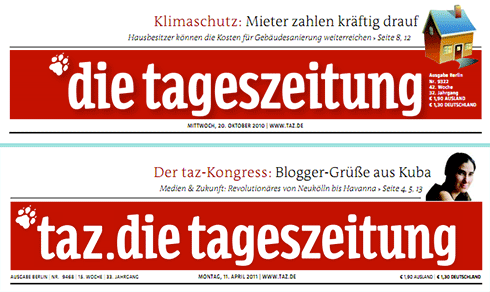
Seit gestern prangt ein neues Logo auf der Titelseite der taz. Sie heißt jetzt nicht mehr nur »die tageszeitung«, sondern »taz.die tageszeitung«. »Die Titelkopfveränderung ist ein großer Schritt für uns gewesen« heißt es im hauseigenen Blog. In den vergangenen Jahren habe die taz unzählige Logos entwickelt: für die Stiftung, den Shop, Kaffee, Genossenschaft, vielfältige redaktionelle Produkte, Reisen und vieles mehr. Dabei sei die visuelle Markenarchitektur eher gewuchert als gewachsen. Deshalb sei derMoment gekommen, die Marken zu sortieren und ihre Verwandtschaft auch visuell herzustellen.
Weiter schreibt Nina Schoenlan im taz-Blog: »Zu jedem Logo hier im Haus gehören Menschen, die dieses Logo gemacht haben, das Projekt hinter dem Logo mit Leben erfüllt haben und zum Strahlen brachten. Deswegen haben wir keine Logos entfernt. Alles wird über einen Punkt mit der taz verbunden. Wir haben mit der Agentur Metadesign Bildmarken integriert, die ›taz‹ konsequenter platziert und verbindende Elemente ausgearbeitet.«
Ist ja kaum noch wiederzuerkennen. Haben sie am Footer auch etwas geändert? Wenn ja war das ja fast ein kompletter Relaunch.
taz.die … tageszeitung? ich versteh’s nicht. statt aufzuräumen verschlimmbessert. *fail*
Ich finde es mißlungen, wenn Begriffe, die Leerzeichen enthalten, durch ein Satzzeichen verbunden werden; „taz.die“ steht hier tatsächlich isoliert von „tageszeitung“. (Vgl. „Forssman/de Jong“)
und wenn schon, dann ja wohl bitte „taz. die tageszeitung.“
bin ja mal auf die bildmarken von metadesign gespannt, die im taz-blog erwähnt werden.
ob die beim neuen titel auch die finger im spiel hatten?
Immerhin wurde der Schatteneffekt entfernt.
@ paul: danke. auch ich finde, daß schatten deutlich überbewertet sind.
warum nicht eigentlich nur »taz«? frage ich mich.
stimme Seppl zu: verschlimmbessert …
Da es hier um die Weiterentwicklung eine Markenfamilie geht, hätte ich diese jetzt ja doch gerne mal im Bild gesehen.
Abgesehen davon verstehe auch ich beim besten Willen nicht, was man uns mit “taz.die” sagen will. Nichts gegen Wortmarken, bei denen einzelne Bestandteile mit Punkten ohne Leerzeichen verbunden werden. Hier funktioniert das aber wegen des bereits vorhandenen Leerzeichens zwischen “die” und “tageszeitung” einfach nicht. Das ist eigentlich ziemlich offensichtlich. Warum wirds trotzdem gemacht?
steckt da wirklich ‹metadesign› hinter?